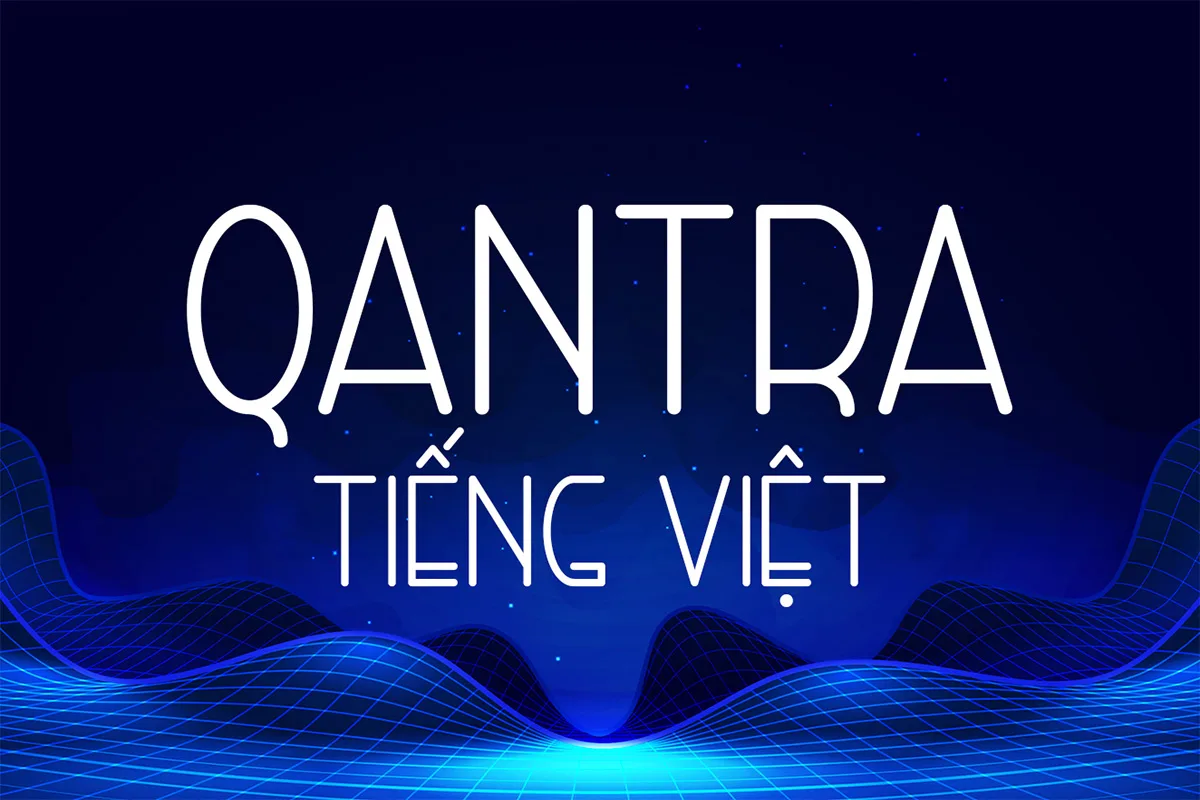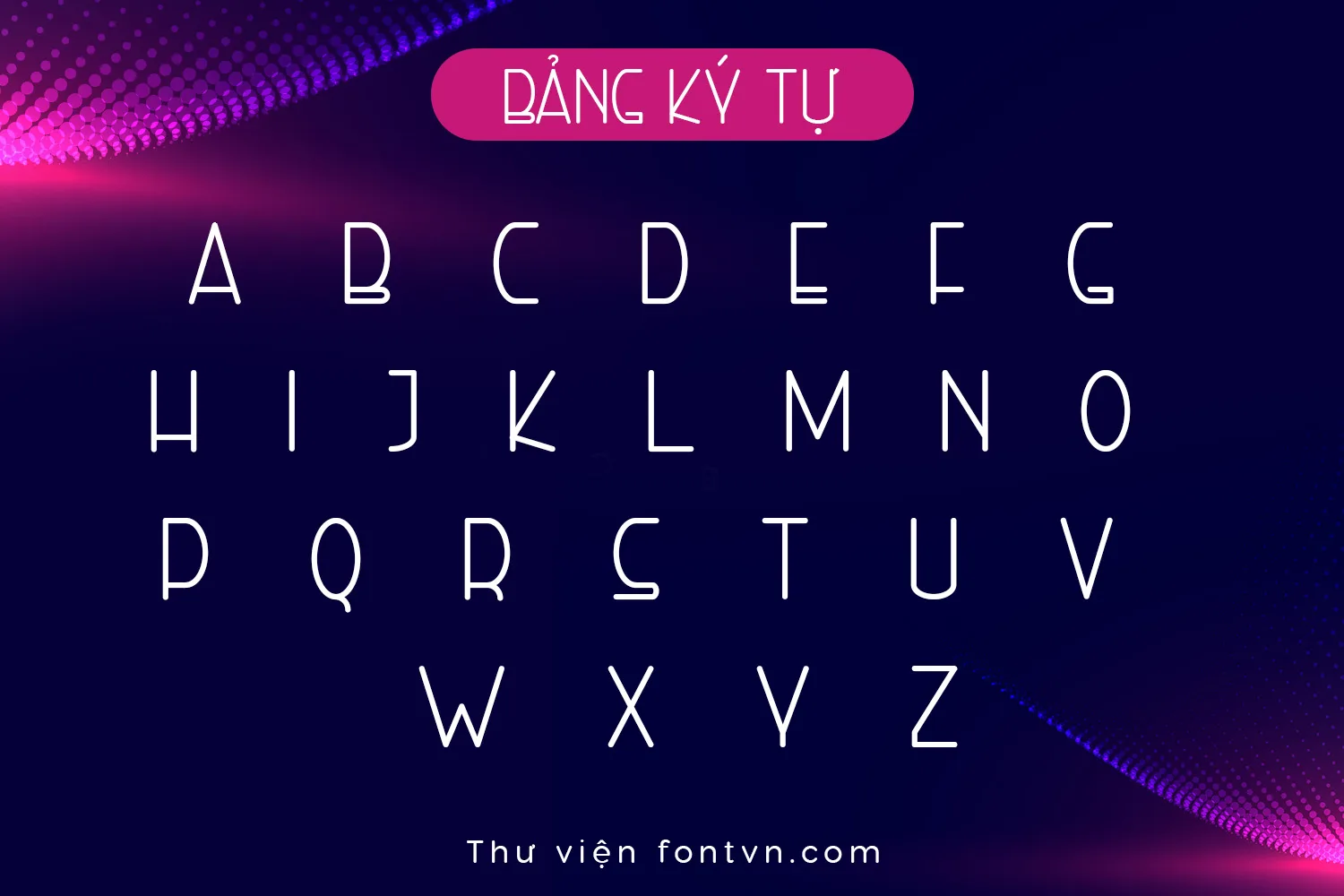
DVN Qantra Tiếng Việt – Modern Futuristic Display Font
DVN Qantra Tiếng Việt là kiểu chữ display mang phong cách futuristic kết hợp tinh thần geometric hiện đại, nổi bật với các đường nét mảnh, cấu trúc cao và độ tương phản hình học tinh tế. Bộ ký tự được thiết kế theo hướng tối giản nhưng giàu cá tính, tạo cảm giác công nghệ, sang trọng và đậm chất thị giác đương đại. Phiên bản Việt hóa được tinh chỉnh đầy đủ dấu tiếng Việt, đảm bảo tính đồng bộ và thẩm mỹ khi sử dụng trong thiết kế chuyên nghiệp.
Font phù hợp cho các dự án branding, poster, tiêu đề, UI/UX, thời trang, công nghệ, gaming, sci-fi và thiết kế editorial hiện đại. Với form chữ thanh thoát cùng khoảng cách thị giác cân đối, DVN Qantra dễ dàng tạo điểm nhấn mạnh mẽ trong các layout tối giản, luxury hoặc cyberpunk mà vẫn giữ được độ đọc rõ ràng và ấn tượng thị giác cao.